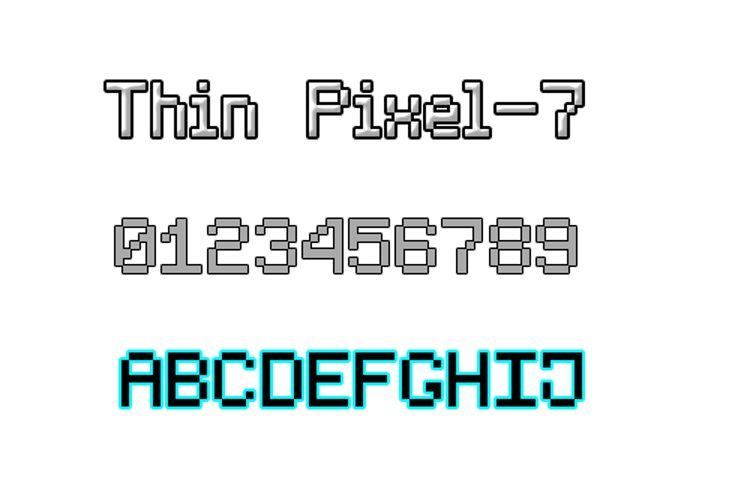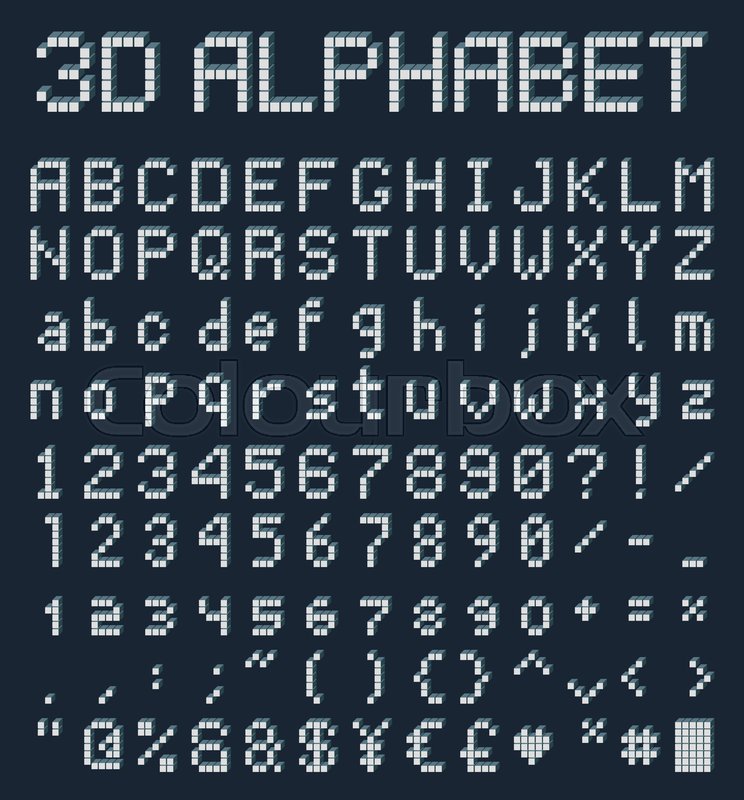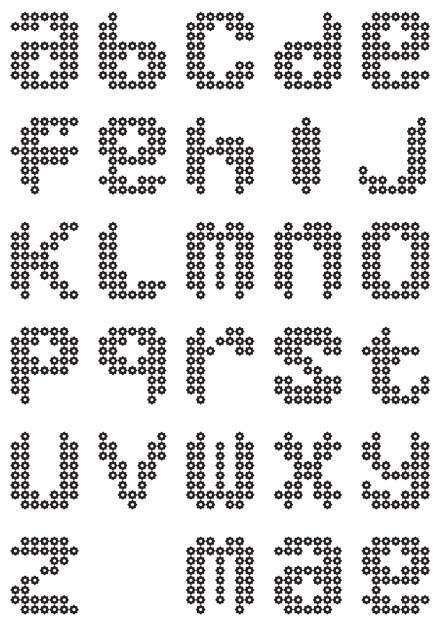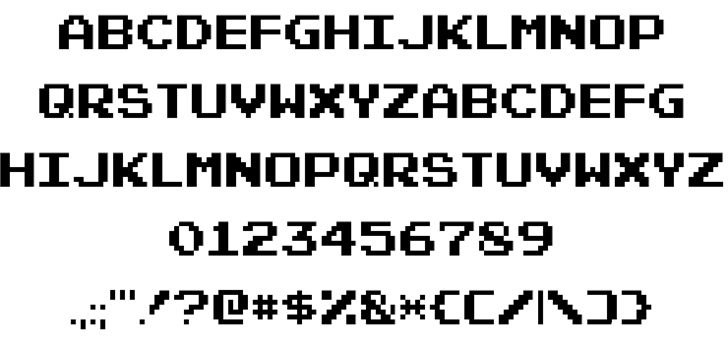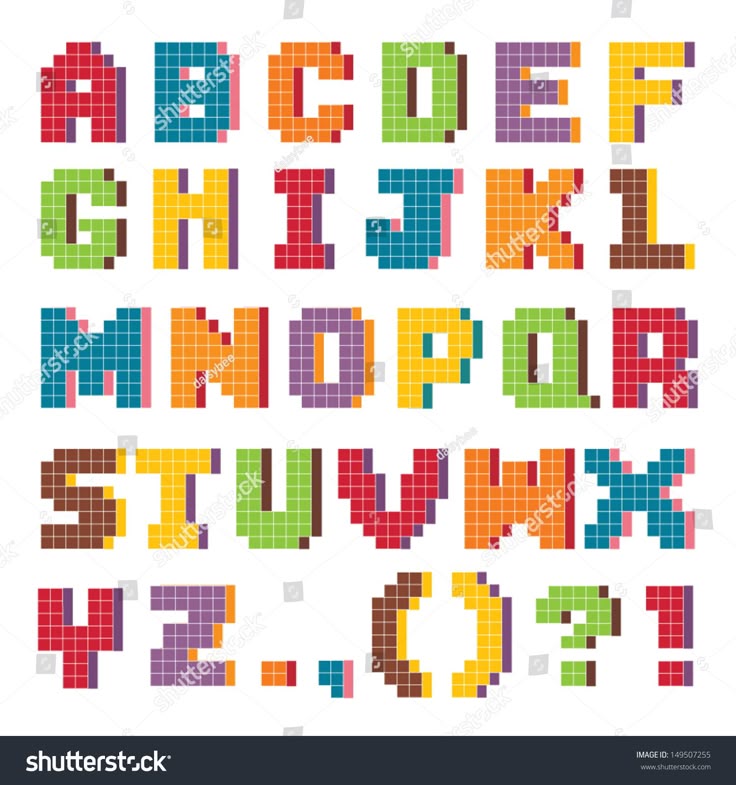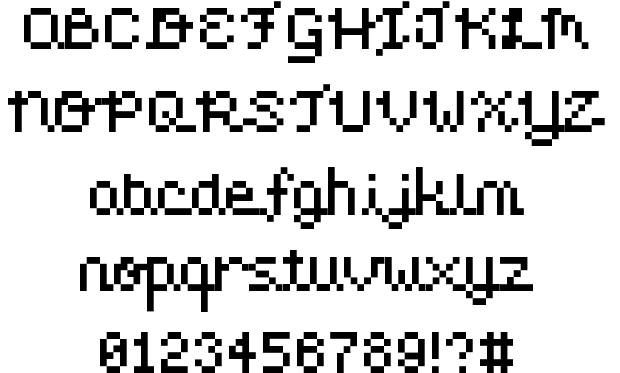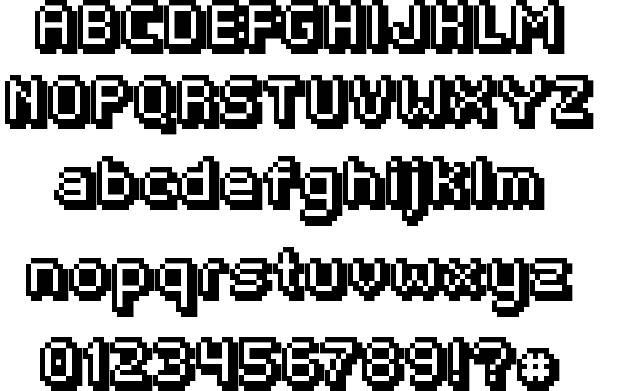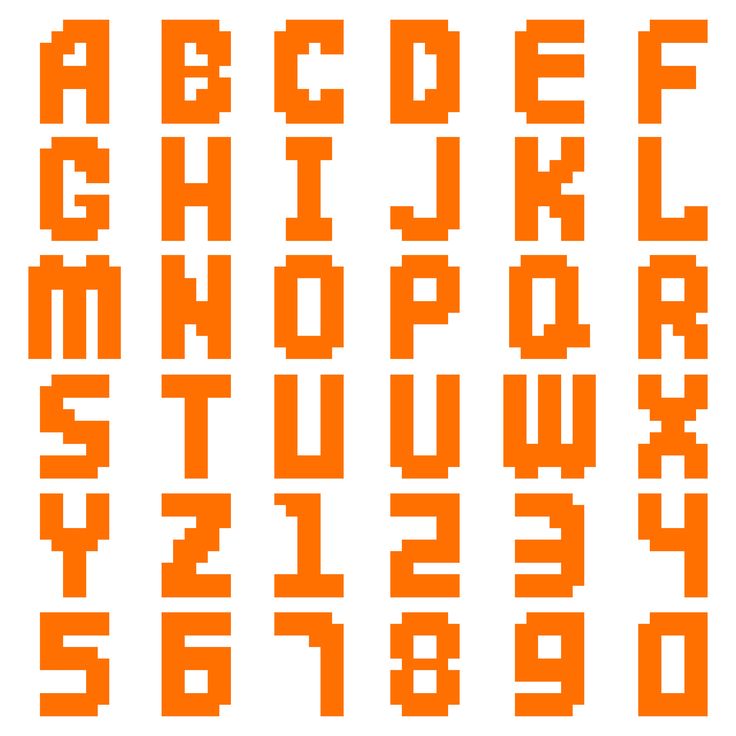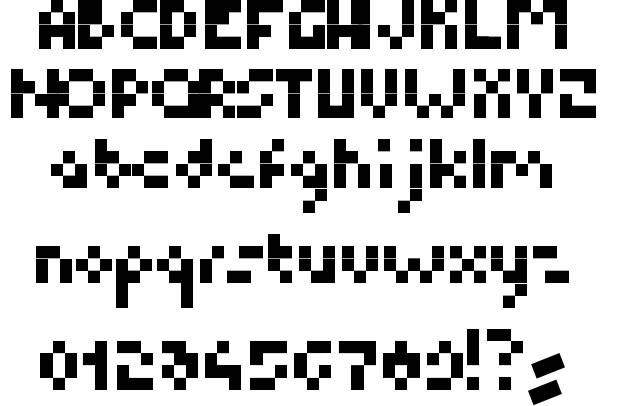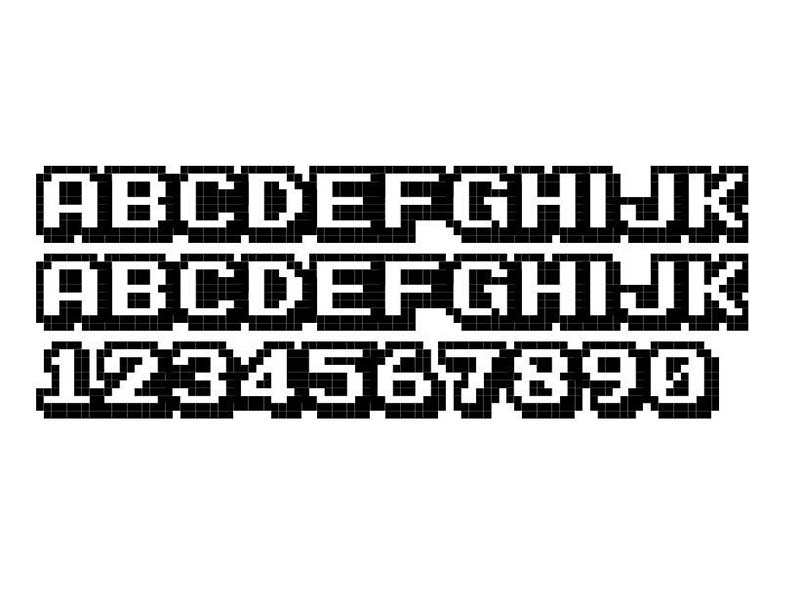
Шрифты несостоявшегося будущего, искусство контрформы и неожиданные предпосылки европейского книгопечатания
Антиква-гротеск для обложек хардкор-панка
Grilli Type выпустили ещё один вариативный сверхшрифт. С одной стороны, Ultra растёт из хрестоматийных гуманистических гротесков, с другой — из выточенных жирных антикв в каталоге Photo-Lettering Inc. При этом гротескная часть семейства получилась более каллиграфическая, а антиквенная — более механистичная, чем упомянутые образцы. Как и следует из названия, Ultra особенно расцветает в сверхжирных начертаниях, где нет курсива и почти нет засечек, зато очень заметно изменение контраста.
Ретрофутуризм от Lineto
Новая коллекция шрифтов Lineto — дань уважения индустриальному, футуристическому, раннецифровому модернизму второй половины XX века. Здесь угловатый вариативный шрифт из леттеринга дорожных служб (Pirelli), модульный червячный шрифт (Rephlex), подслеповатый пиксельный шрифт с закруглениями (Moonbase), точечный шрифт с завораживающей модуляцией (DMT) и шрифт из леттеринга с названием Чернобыльской АЭС (Atomgrad, с кириллицей нарисованной Евгением Анфаловым и Викторией Грабовской).
Halunke в айдентике Эль-Класико
Эль-Класико — дерби «Барселоны» и «Мадрида», главный матч испанской футбольной лиги. В этом году Эль-Класико пройдёт 24 октября, и у него есть собственная айдентика — на основе шрифта Halunke из нашего каталога tomorrow. В сентябре партизанская промокампания Эль-Класико — эмблема из нескольких глифов Halunke появлялась на бесхозных стенах по всему миру — получила награду Sports Industry Awards. Айдентика была разработана агентством Vasava, специально для проекта автор Halunke Элена Шнайдер немного модифицировала шрифт.
Контрформы, жирность, кернинг и трекинг
Шрифтовой дизайнер Райли Крэн (Lettermatic) написал три очень познавательных треда в твиттере о контрформах (негативном пространстве), специфике рисования жирных начертаний и межбуквенном расстоянии (кернинге и трекинге).
Кратко, просто, с иллюстрациями — прекрасный материал для самообучения. P. S. В прошлом месяце Lettermatic выпустили большой рассказ про создание шрифта для игры Psychonauts 2 — он тоже достоин самого обстоятельного чтения.
Злой
Шрифт Zloy Дарьи Петровой, про который мы писали в прошлом дайджесте, теперь выставлен на витрине tomorrow — как обычно, можно скачать бесплатную пробную версию.
Лекции Дениса Машарова
Денис Машаров (1973–2021) известен как один из лучших рассказчиков о шрифте и типографике на русском языке. Студия Letterhead собрала в единый плейлист лекции Дениса на ютьюбе (в том числе три недавно загруженных Сергеем Рассказовым), а школа Bang Bang Education открыла бесплатный доступ к онлайн-курсу Дениса (для просмотра требуется регистрация на сайте).
The message to Ukraine
Агентство Obys выпустило зин к 30-летию Украины в августе, а в сентябре он получил награду Awwwards Site of the Day. Внимания здесь заслуживает продуманная сетка и анимация, сдержанные цвета, простая (но выразительная) типографика и полезный список украинских дизайн-студий.
Еще один набор креативных пиксельных шрифтов. Этот шрифт поставляется в двух стилях: с обычными полыми буквами в стиле пиксельной графики и в другой версии с заполняющими буквами. Оба шрифта имеют стильные надписи в стиле пиксель-арт. Его можно использовать совершенно бесплатно.
Этот пиксельный шрифт отличается креативным дизайном букв, вдохновленным ретро-видеоиграми.![]()